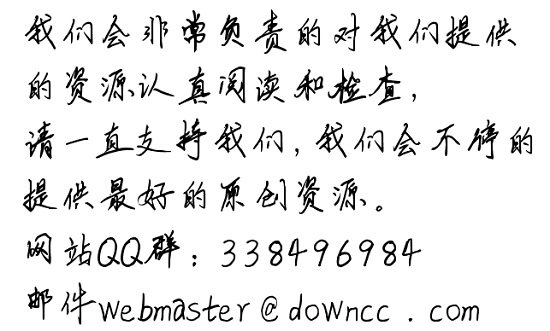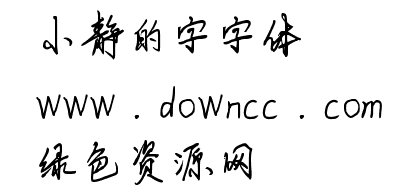
小靜的字字體是思雨字庫推出的一款干凈簡潔的手寫字體,給人優(yōu)雅安然的現(xiàn)世寧靜之感,讓文字更加清新質(zhì)樸,字跡鮮明,喜歡的朋友就來綠色資源網(wǎng)試試吧!
小靜的字出自思雨字體,字跡流暢而娟秀,讓人從眾品嘗到安然悠閑的恣意,給人十分生動純粹的視覺體驗,讓你的平面設(shè)計、包裝設(shè)計、藝術(shù)設(shè)計等效果突出。
小靜的字,靜靜的字!換一種字體換一種心情!
本字庫是在國家標(biāo)準(zhǔn)簡體字庫GB2312所包含6763漢字的基礎(chǔ)上,又增加了近200常用字,已經(jīng)覆蓋了大陸99.75%的漢字使用頻率,足以滿足日常需求。喜歡就五星好評,您的支持是我們最大的動力!